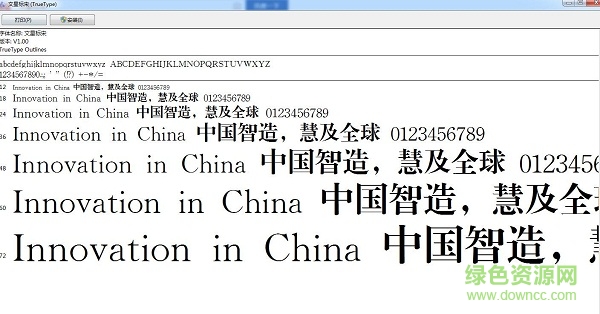
wxxbs是什么字體?wxxbs字體是一款結(jié)構(gòu)飽滿的標宋字體,筆鋒簡潔,字形端正,適用于電子手冊、報刊、辦公文件等方面,歡迎大家在本站免費下載!
這款字體中宮略為收緊,整體風(fēng)格醒目現(xiàn)代,不但適用于各類傳統(tǒng)紙媒,因其橫豎筆畫粗細適度,還可直接用于屏幕閱讀。